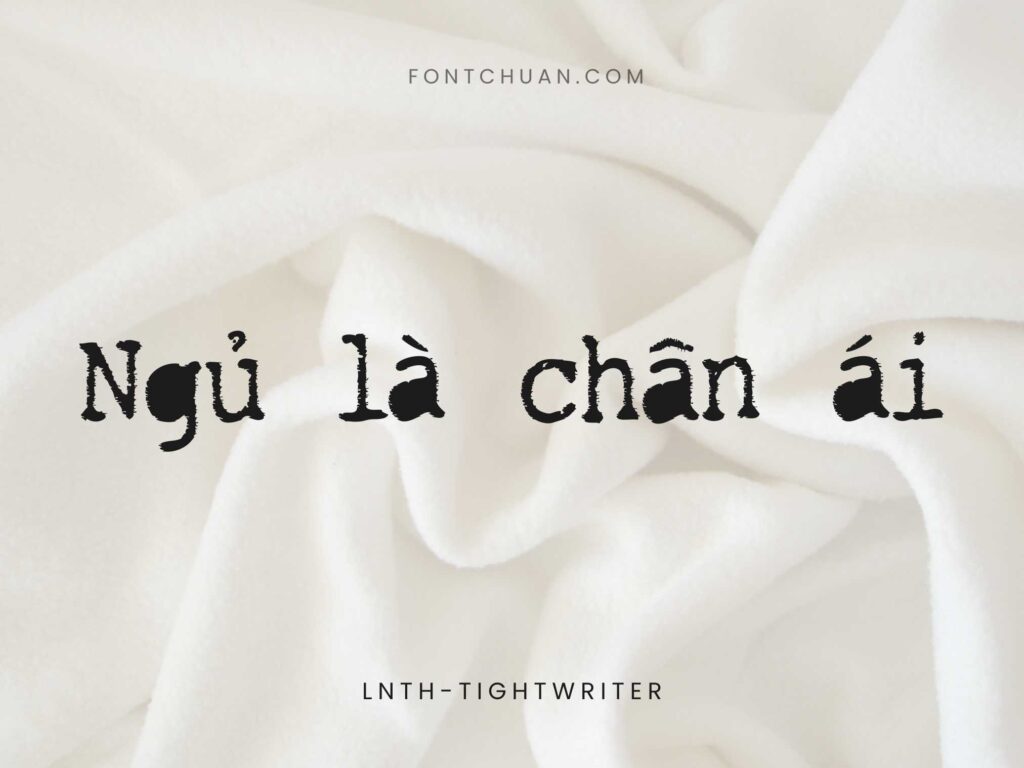
Font LNTH Tight Writer Việt Hóa
Font Tight Writer là một Font Monospace mang phong cách cổ điển, lấy cảm hứng từ các máy đánh chữ truyền thống. Với thiết kế góc cạnh, sắc nét nhưng vẫn giữ được sự mượt mà trong từng nét chữ, Tight Writer mang lại cảm giác hoài cổ nhưng vẫn phù hợp với các thiết kế hiện đại. Font này rất thích hợp cho các dự án liên quan đến văn bản kiểu retro, thiết kế báo chí hoặc nội dung mang phong cách vintage.
Phiên bản này đã được Việt hóa bởi LNTH, hỗ trợ đầy đủ tiếng Việt cùng hơn 50 ngôn ngữ khác, giúp người dùng dễ dàng ứng dụng trong thiết kế quốc tế. Font Tight Writer được các thành viên Font Chuẩn sưu tầm và đăng tải nhằm cung cấp một lựa chọn độc đáo cho các thiết kế mang hơi hướng hoài cổ và chuyên nghiệp.
Về đặc điểm thiết kế, Tight Writer có cấu trúc monospace đều đặn, từng ký tự được căn chỉnh chính xác, giúp tạo ra sự cân đối và dễ đọc. Font này đặc biệt phù hợp để sử dụng trong các thiết kế văn bản dài, tài liệu chuyên môn, thiết kế retro, hoặc các dự án mang phong cách cổ điển.
Font Tight Writer được ứng dụng rộng rãi trong các sự kiện như báo chí, thiết kế văn phòng, hoặc các dự án mang phong cách vintage. Nó phù hợp với nhiều ngành nghề như quảng cáo, giáo dục, công nghệ và bất động sản.